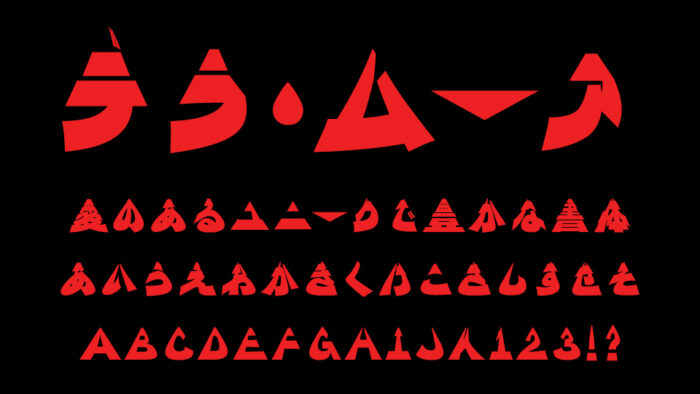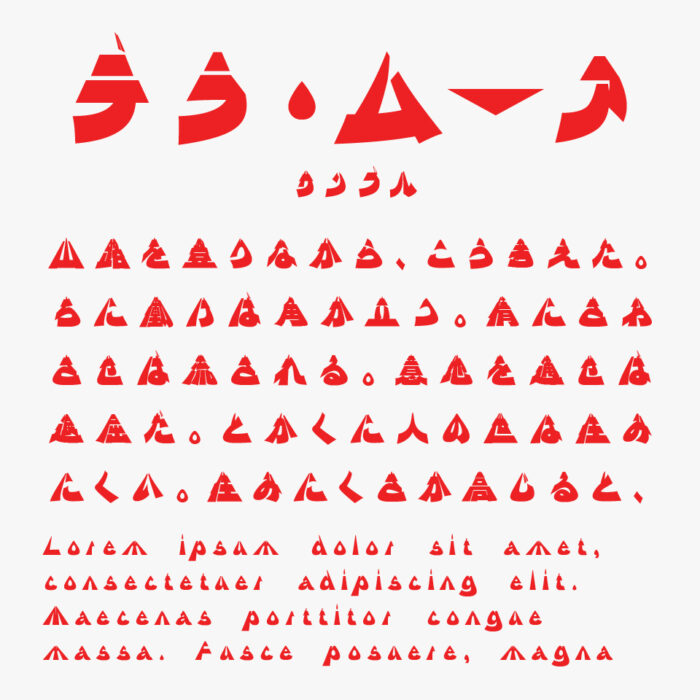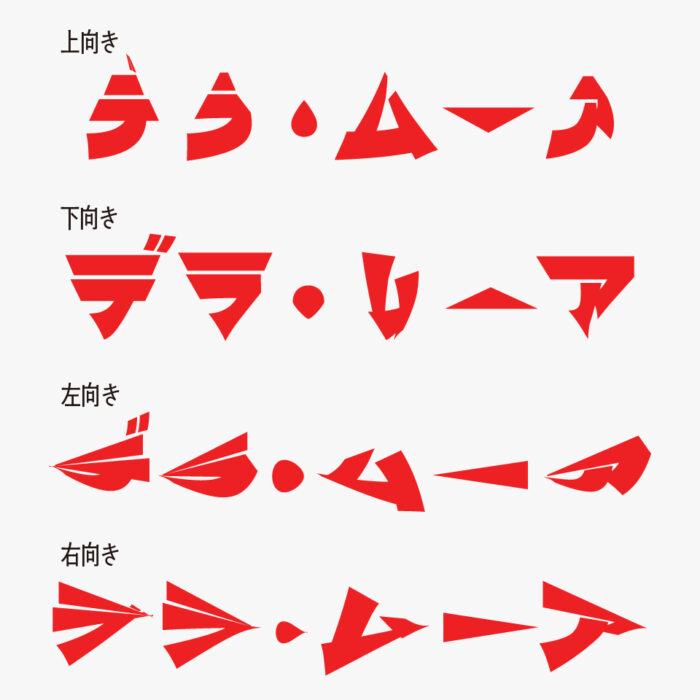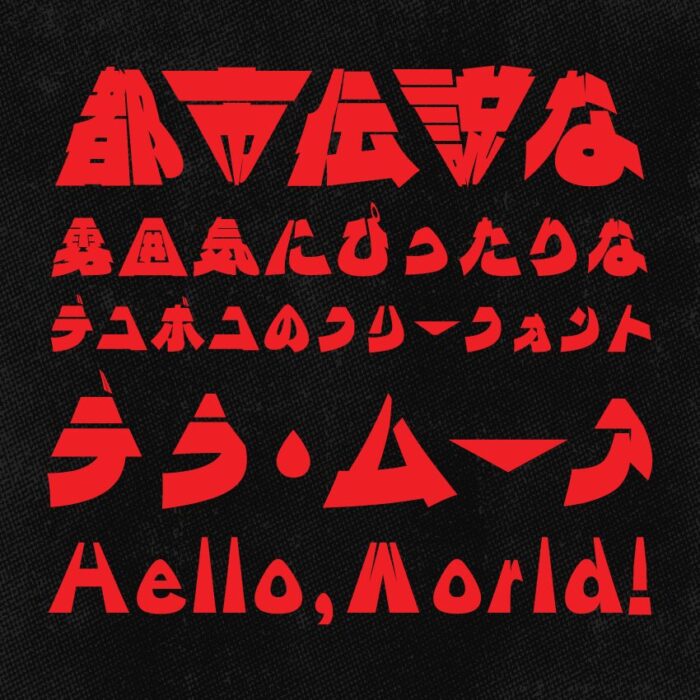
デラ・ムーアフォントは、デラゴシックをベースに、鋭角的で独特なシルエットに変形加工させた目を引くデザインフォントです。
文字が幾何学的にデフォルメされていることで、暗号やヒエログリフのような独自の雰囲気をもつユニークで面白いデザインとなっています。
デラ・ムーア
上向きに変形されているだけではなく、下向き・右向き・左向きといった上下左右に変形したものも揃っています。
デラ・ムーア
組み合わせ使うことで、デコボコ感のある使い方もできます。某都市伝説系雑誌のロゴな雰囲気もあることで、都市伝説系ジャンルにもハマりそうなフォントです。
デラ・ムーア